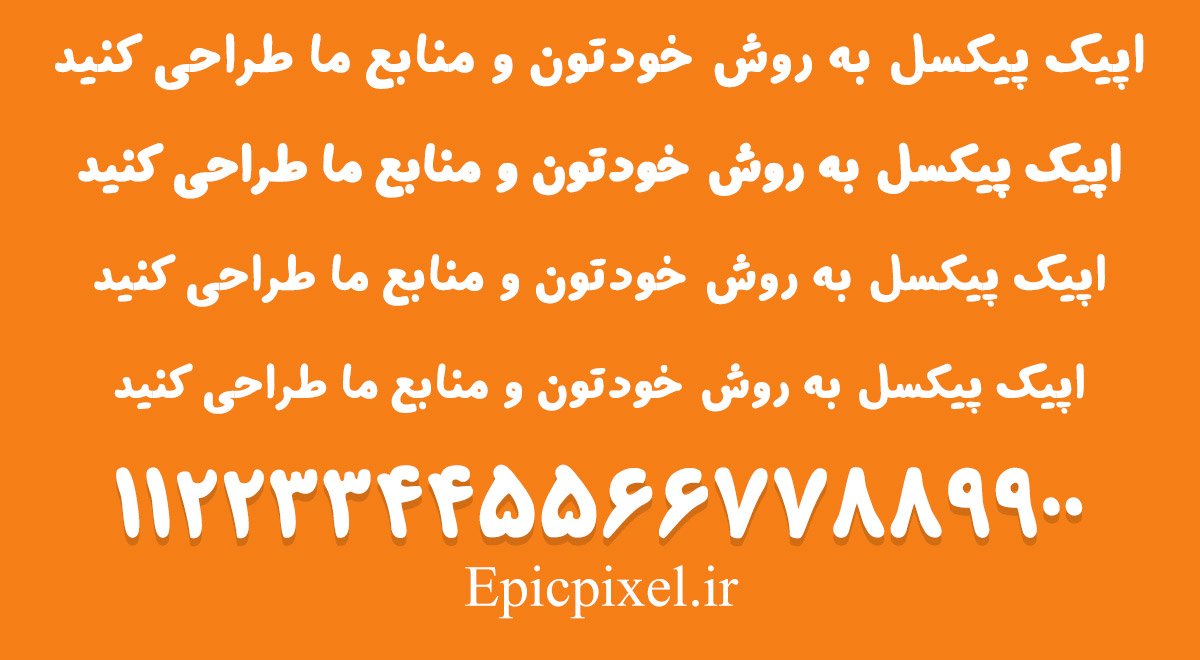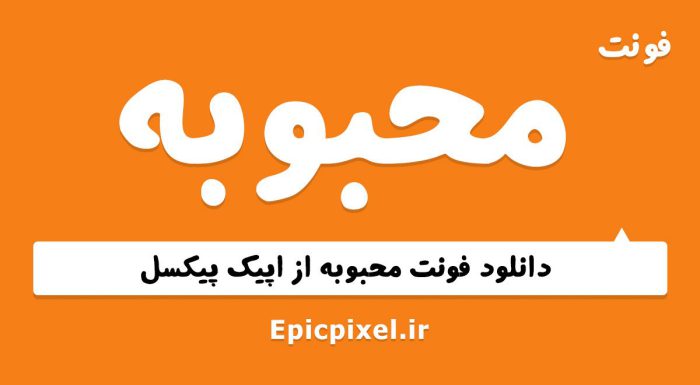
فونت محبوبه فارسی
فونت محبوبه مهر آور
سلام به همه دوستان علاقه مند به زیبایی نوشتار. امروز با شما هستیم با معرفی یک فونت جدید و جذاب که می تواند به شما کمک کند تا متن های خود را با سبک دست نویس بنویسید. این فونت که فونت محبوبه مهر آور نام دارد، توسط خانم محبوبه مهرآور، یک خطاط و طراح گرافیک حرفه ای، طراحی شده است. در این مقاله قصد داریم به شما بگوئیم که این فونت چه خصوصیاتی دارد، چگونه طراحی شده است، چگونه می توانید آن را دانلود و استفاده کنید و چه نمونه هایی از آثار گرافیکی با استفاده از این فونت ساخته شده است. پس با ما همراه باشید.
معرفی فونت مهر آور
فونت محبوبه مهر آور یک فونت دست نویس است که برای نگارش متن های عامیانه، طنز و ادبیات کودک و نوجوان مناسب است. این فونت با الهام از سبک قلم های نسخ ساخته شده است و دارای خلاقانگی و جذابیت بالایی است. این فونت در سال 1394 تولید شده است و در حال حاضر به صورت رایگان قابل دانلود و استفاده است.
خصوصیات فونت مهراور
سبک دست نویس
این فونت با سبک دست نویس طراحی شده است که به متن ها حال و هوای غیر رسمی و صمیمانه ای می دهد. این سبک برای نوشتن متن هایی که مخاطب را درگیر و مشتاق کند مناسب است. برای مثال، می توانید از این فونت برای نوشتن داستان های کوتاه، شعر، کارت پستال، بنر تبلیغاتی، کاور کتاب و مجله و غیره استفاده کنید.
مناسب برای متن های عامیانه، طنز و ادبیات کودک و نوجوان
این فونت با توجه به سبک دست نویس و خط نسخ طراحی شده است که برای متن های عامیانه، طنز و ادبیات کودک و نوجوان انتخاب مناسبی است. این فونت می تواند به شما کمک کند تا متن های خود را با روحیه ای شاد و سرزنده بنویسید. برای مثال، می توانید از این فونت برای نوشتن داستان های خنده دار، شعر های طنز، کارت پستال های تبریک، بنر های تبلیغاتی جذاب، کاور کتاب ها و مجلات کودک و نوجوان و غیره استفاده کنید.
این فونت با الهام از چوب گوش پاک کن به جای قلم طراحی شده است که نشان دهنده خلاقیت و جذابیت طراح فونت است. این فونت با استفاده از خط نسخ ساختار منظم و متناسبی دارد که خوانایی را افزایش می دهد. این فونت با تغییرات جزئی در حروف و حالات مختلف آن ها، حس تنوع و زیبایی را به مخاطب منتقل می کند. برای مثال، می توانید از این فونت برای نوشتن عبارات هنری، لوگو، سربرگ، تصاویر گرافیکی و غیره استفاده کنید.
خوانایی بالا
این فونت با توجه به سبک دست نویس طراحی شده است اما خلاف بسیاری از فونت های دست نویس دیگر، دارای خوانایی بالایی است. این فونت با رعایت ساختار قلم های نسخ و استفاده از حروف با ابعاد مناسب، فضای خالی لازم را بین حروف و کلمات ایجاد می کند. این فونت با حفظ تعادل بین حال و هوای دست نویس و خط نسخ، مانع از پدید آمدن حس سردرگمی و خستگی در خواندن متن ها می شود. برای مثال، می توانید از این فونت برای نوشتن مقالات، گزارش ها، رمان ها، دفترچه راهنما و غیره استفاده کنید.
قابل استفاده در آثار گرافیکی و تبلیغاتی
این فونت با توجه به سبک دست نویس و خط نسخ طراحی شده است که برای استفاده در آثار گرافیکی و تبلیغاتی مناسب است. این فونت با ایجاد تضاد بین سبک دست نویس و خط نسخ، حس جالب و متفاوتی را به مخاطب منتقل می کند. این فونت با استفاده از رنگ ها، بافت ها، تصاویر و عناصر گرافیکی دیگر، قابل تنظیم و تطبیق با هر نوع طرح گرافیکی است. برای مثال، می توانید از این فونت برای طراحی پوستر، بروشور، کاتالوگ، بسته بندی، لوگو و غیره استفاده کنید.
نحوه طراحی فونت
ایده استفاده از چوب گوش پاک کن به جای قلم
این فونت با الهام از چوب گوش پاک کن به جای قلم طراحی شده است. این ایده نشان دهنده خلاقیت و جسارت طراح فونت است که با استفاده از یک وسیله ساده و رایج، یک فونت جدید و جذاب را خلق کرده است. این ایده باعث شده است که حروف این فونت دارای حالات مختلف و جذاب باشند که به متن ها حس تازگی و شور می دهد.
این فونت با توجه به ساختار قلم های نسخ کتابت شده است. قلم های نسخ از جمله قلم های رسمی و معروف در خط فارسی هستند که دارای ساختار منظم و متناسب هستند. خطاط محبوبه مهرآور با رعایت قوانین خط نسخ و استفاده از حروف با ابعاد مناسب، فونتی را طراحی کرده است که دارای خوانایی بالایی است. این فونت با حفظ ساختار قلم های نسخ، مانع از پدید آمدن حس سردرگمی و خستگی در خواندن متن ها می شود.
کنترل شده و متناسب
این فونت با توجه به سبک دست نویس طراحی شده است اما خلاف بسیاری از فونت های دست نویس دیگر، دارای کنترل شده و متناسب بودن است. خطاط محبوبه مهرآور با رعایت تعادل بین حال و هوای دست نویس و خط نسخ، فونتی را طراحی کرده است که دارای حس جالب و متفاوتی است. این فونت با تغییرات جزئی در حروف و حالات مختلف آن ها، حس تنوع و زیبایی را به مخاطب منتقل می کند.